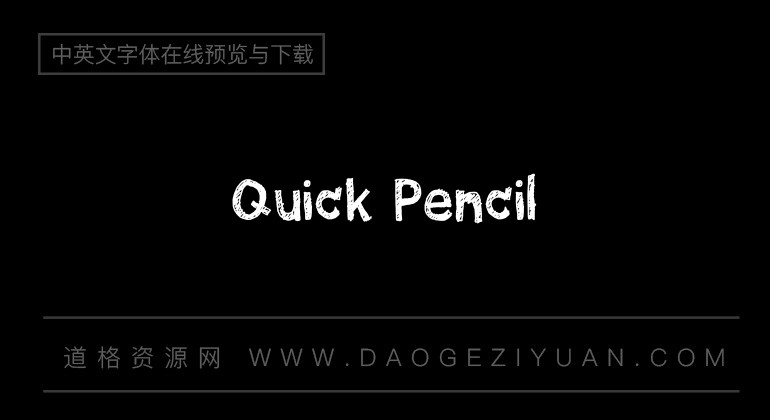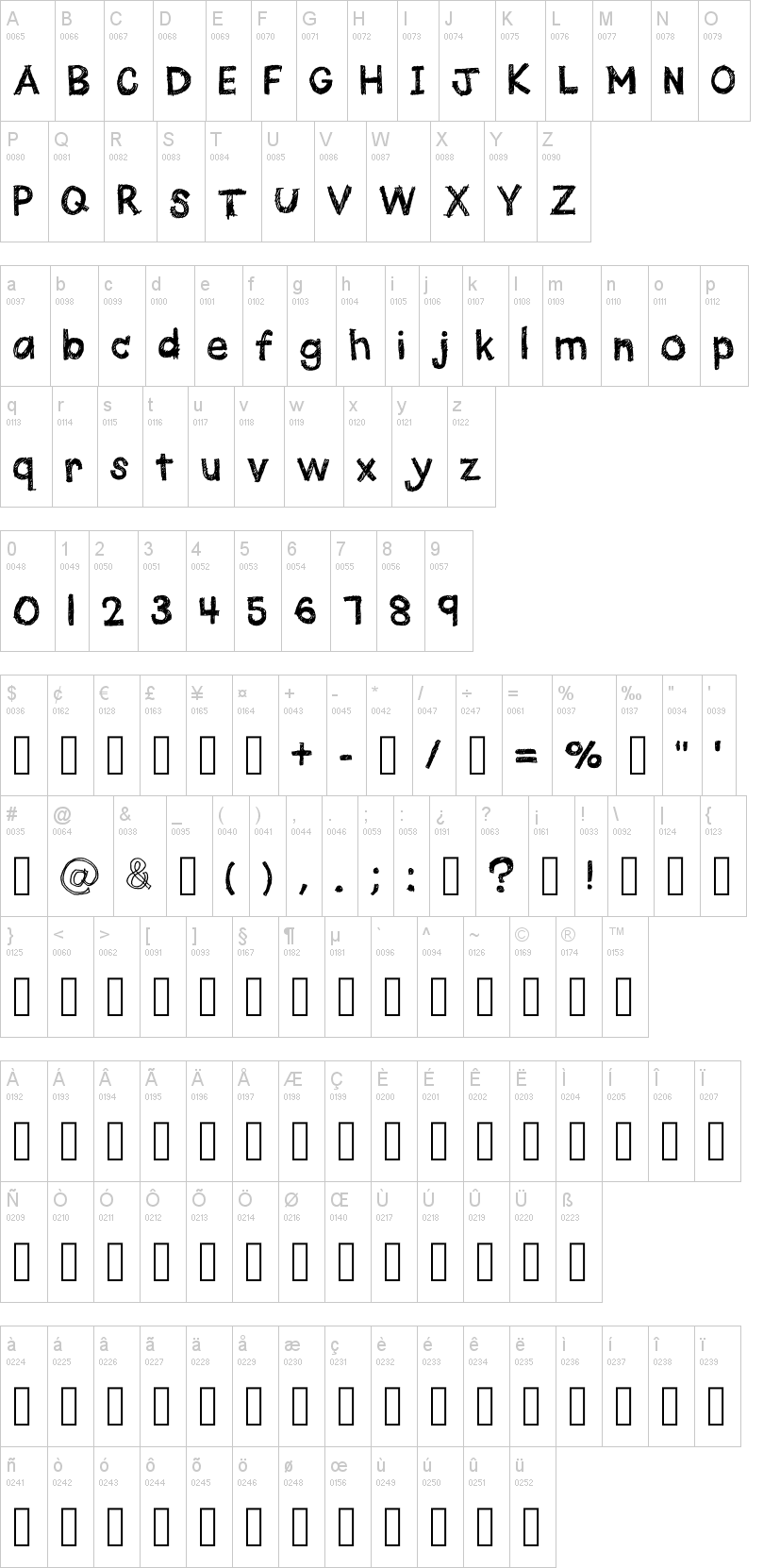
Quick Pencil
? Quick Pencil是一款涂鸦风格的字体,具有灵活的可定制的形状,可以提供更多的设计灵活性,可以让你的设计更加有趣,活泼,充满活力。它有一种抽象的,粗犷的风格,可以为你的设计提供独特的外观,令人印象深刻。它适合用于任何形式的设计,尤其是涂鸦风格的设计。
Quick Pencil是一款非常不错的手写艺术字体,具有很好的视觉感,适合于文化类的宣传设计、商业类品牌的广告和产品包装设计以及个性化文字排版等较多场景。
Quick Pencil字符映射图